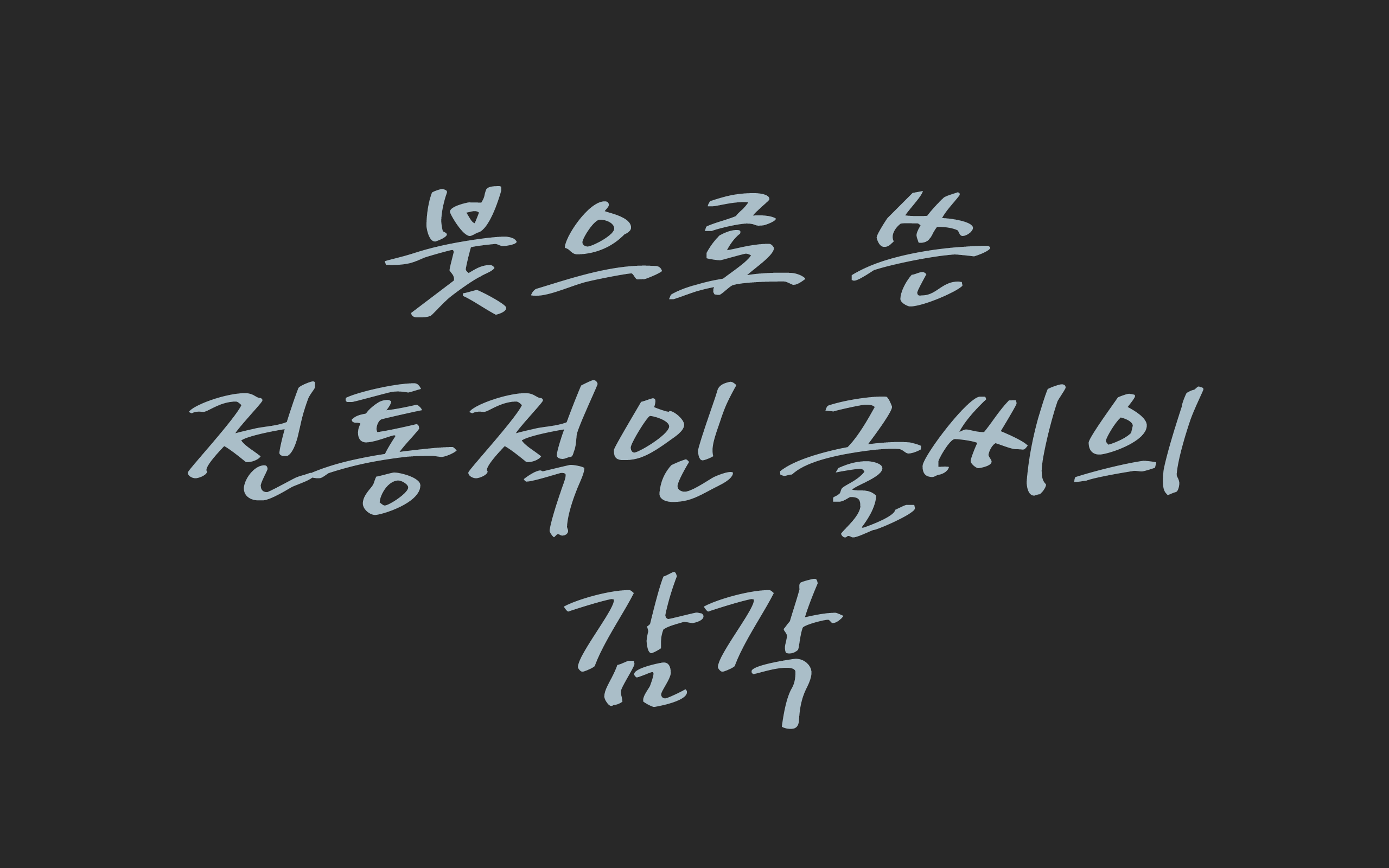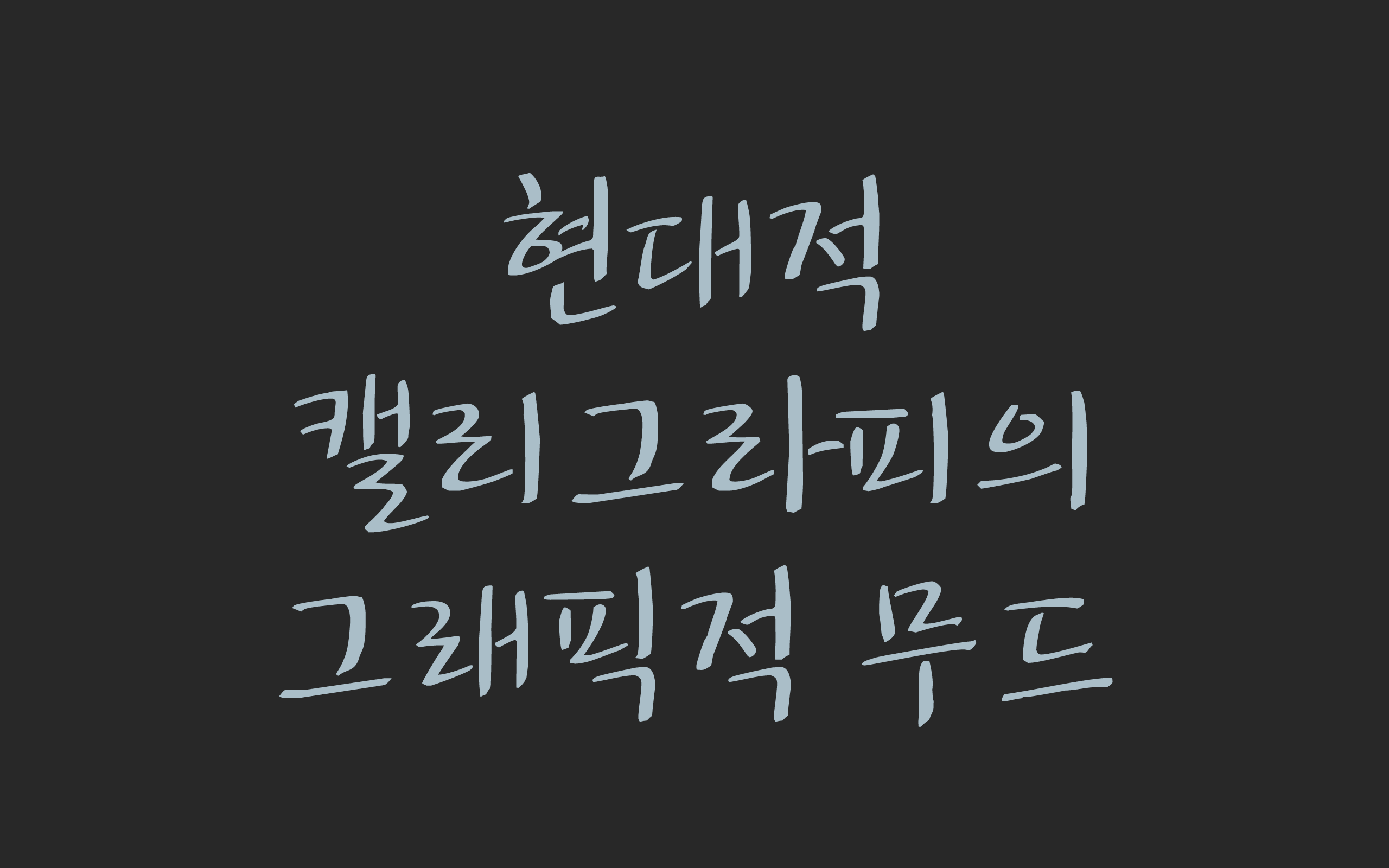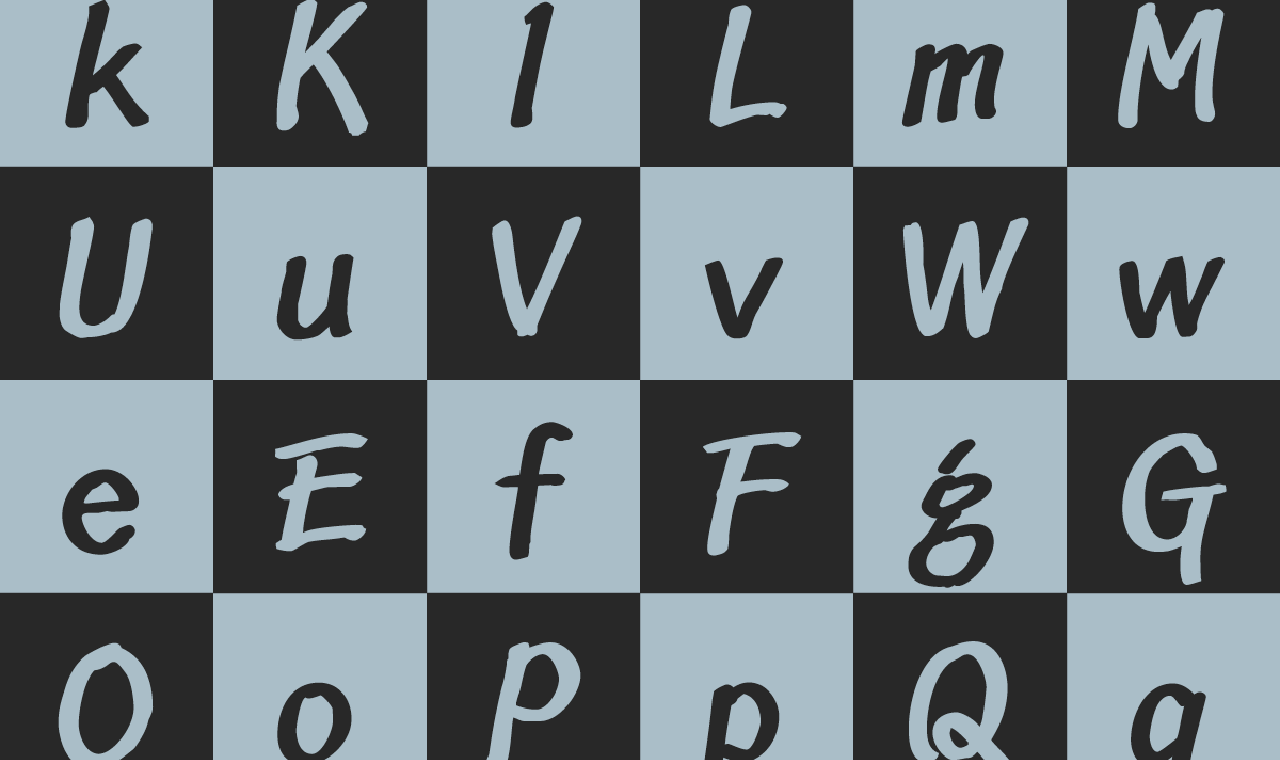
붓의 필력을 재현한 자유와 그래픽적 무드가 살아 있는 갈채, 전통 붓글씨와 현대적 캘리그래피 사이의 접점을 모색하는 윤디자인×김익원 아티스트 폰트 콜렉션
아티스트 콜렉션 김익원 정통 붓글씨와 현대적 캘리그래피
김익원은 전통 서예 국전 초대 작가로 활약하는 동시에 〈어느 멋진 날〉, 〈거침없이 하이킥〉,
〈코끼리〉, 〈품바 1000일의 기록〉 등 방송 타이틀 제작 디자인을 담당한 바 있습니다.
전통과 현대를 아우르는 이력처럼 작업 또한 전통과 현대를 접목하여, 회화성이 돋보이는 서예,
전통 운필에 캘리그래피 감각을 더한 독창적 필체를 선보이지요.
붓으로 쓴 전통적인 글씨의 감각
전통 붓글씨와
현대적 캘리그래피의 만남
자유, 갈채로 구성된 김익원 아티스트 폰트 콜렉션에는 붓으로 쓴 전통적인 글씨의 감각과 현대적 캘리그래피의 그래픽적 무드가 탁월한 균형감을 유지하며 나란히 녹아들어 있습니다. 자유는 자유분방한 붓글씨의 획을 그래픽적으로 표현한 폰트로 산뜻하고 정적인 표현 방식을, 갈채는 그래픽적 감성보다 붓글씨의 필력을 강조한 폰트로 운동성 있는 역동적인 이미지의 표현 방식을 제안합니다.
서로의 특징을 보완하는
조화로운 콜렉션
이처럼 전통 붓글씨와 현대적 캘리그래피 사이의 접점을 모색하는 자유와 갈채는 서로의 특징을 보완하며 조화로운 하나의 콜렉션을 구성합니다. 전통과 현대의 공존에 대한 근본적 고민이 담겨 있는 김익원 아티스트 폰트 콜렉션과 함께 경계를 자유롭게 넘나들어보시죠.
현대적 캘리그라피의 그래픽적 무드
김입원의 작업들 거침없이 하이킥, 어느 멋진날about font자유분방한 붓글씨 자유L
자유L
자유분방한 붓글씨 자유M
자유M
자유분방한 붓글씨 자유B
자유B
자유분방한 붓글씨의 획을 그래픽적으로 산뜻하게 표현한 폰트입니다.
가로획과 세로획의 굵기 차이를 많이 두어 캘리그래피적 개성을 살리고자 했습니다.
역동적인 붓글씨 갈채M
갈채M
역동적인 붓글씨 갈채B
갈채B
붓글씨의 질감과 필력을 강조하여 역동적인 에너지를 전달하는 폰트입니다.
획의 속도감을 강조하여 캘리그래피의 생동감을 전달하고자 했습니다.